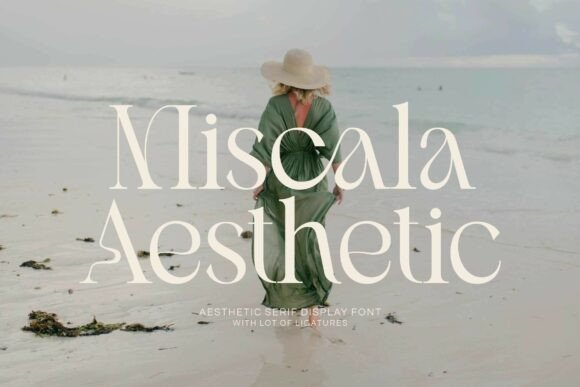
Miscala Aesthetic
Пошук відповідних елементів дизайну може бути складним, але Miscala Aesthetic пропонує виняткову колекцію, яка миттєво покращить вашу роботу.
Незалежно від того, чи створюєте ви продукти POD (друк на вимогу), весільні запрошення або графіку для соціальних мереж, Miscala Aesthetic стане ідеальним вибором.